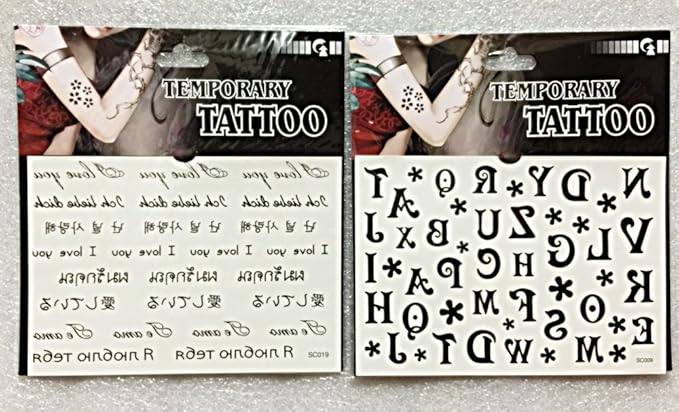
Frutigerを模倣したフォントの1つです。サンセリフ体でありgやyの文字が少しカーブがかっているのが特徴で可愛らしく上品な印象を与えてくれます。アップルや アドビシステムズ (現在アドビはAdobeCleanが利用されて居るとのことです。 。※コメント欄yuki様より)が.
フォント タトゥー 文字 種類. 力強い感じの筆記体刺繍フォント。オールラウンドに使えます。 6 old english(オールドイングリッシュ) 花文字、ドイツ文字などとも呼ばれる書体です。 7 egyptian(エジプシャン) セリフ体(ゲタ文字)太く力強い書体です。 8 egyptian2(エジプシャン2). - Pinterest で 美里 松田 さんのボード「タトゥーのフォント」を見てみましょう。。「タトゥー, タトゥーのフォント, フォント」のアイデアをもっと見てみましょう。. 東京都新宿区のタトゥースタジオ「 fox gate tattoo -狐門刺青処- 」 約10年間、新宿の老舗tattooスタジオを牽引してきた正彩、彫さとが新しく 「fox gate tattoo」をオープン致しました。.
Vid's Norseはラテン文字の代わりに北欧ルーン文字を使用するTTFフォントなので、あなたのバイキングにぴったりのタトゥーフォントです。 商用利用も無料で、スクリーン上とおそらく皮膚上の両方でシャープに見える。 ダウンロード. - 東京新宿fox gate tattoo。「タトゥー, 文字 レタリング, 東京 新宿」のアイデアをもっと見てみましょう。. 文字列内の「一番高い部分」から「一番低い部分」までの 描画エリアを文字サイズとさせていただいております。 上記の理由によって文字サイズのご指定は、同じ列内の 文字の大きさを全て均等に揃えるものではございません。.
はじめに 文字を使ったデザインを行う際には、沢山のフォントの中から一つを選択しなくてはなりません。 ですが大量にインストールされているフォントを一つ一つ確認していると、 非常に時間がかかり、効率が悪くなってしまいます。 よく使われているフォントや、自分が使いやすい. アリアナ・グランデが「七輪」というタトゥーを入れたことで物議を醸し、Twitter上ではその賛否については議論が交わされた。 ここで「ああ、外国の方で漢字のタトゥーね…」と考えるのを辞めてしまうのは、非常に勿体無い。 今回はアリアナ・グランデの一件の考察を通し、漢字のタトゥー. タトゥーで人気の文字デザインならコレでしょ! オールドイングリッシュ ドイツ文字であり「フラクトゥール」とも呼ばれていて、重圧感のある書体が特徴。 筆記体 タトゥーの文字デザインの中でも特に人気が筆記体のフォント。.
Adobe Fonts はサブスクリプション形式のフォントライブラリです。世界の優れたフォントメーカーと提携して美しいフォントを提供します。お気に入りのフォントをライブラリから選択して、アドビのサービスを使用してWebサイトでホストしたり、デスクトップアプリケーション上で使用するため. フォントは、文字の先端に 「ひげ」または 「うろこ」と呼ばれる 装飾の有無によって、大きく2種類に分類 できます。 セリフ体の特徴.